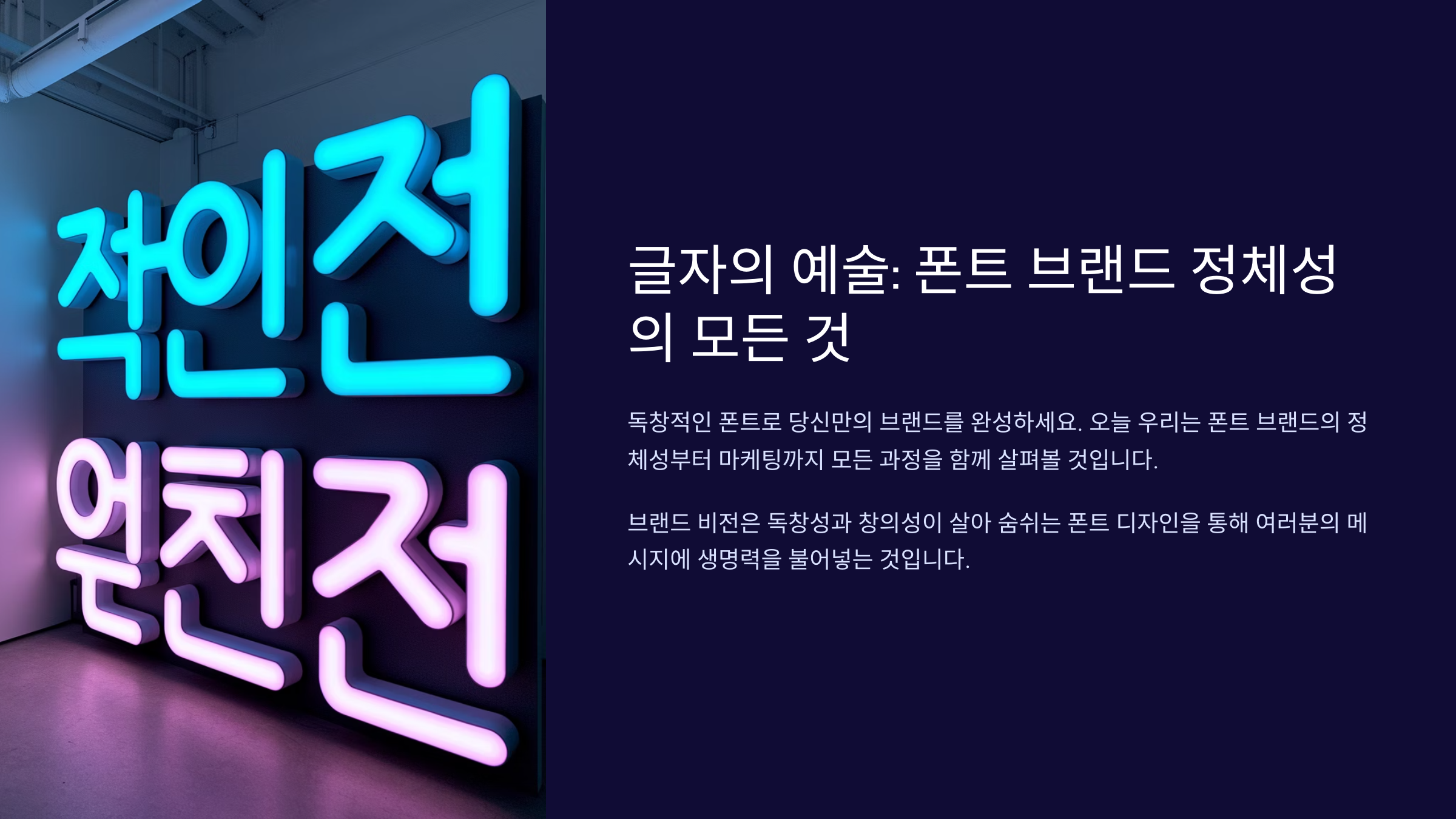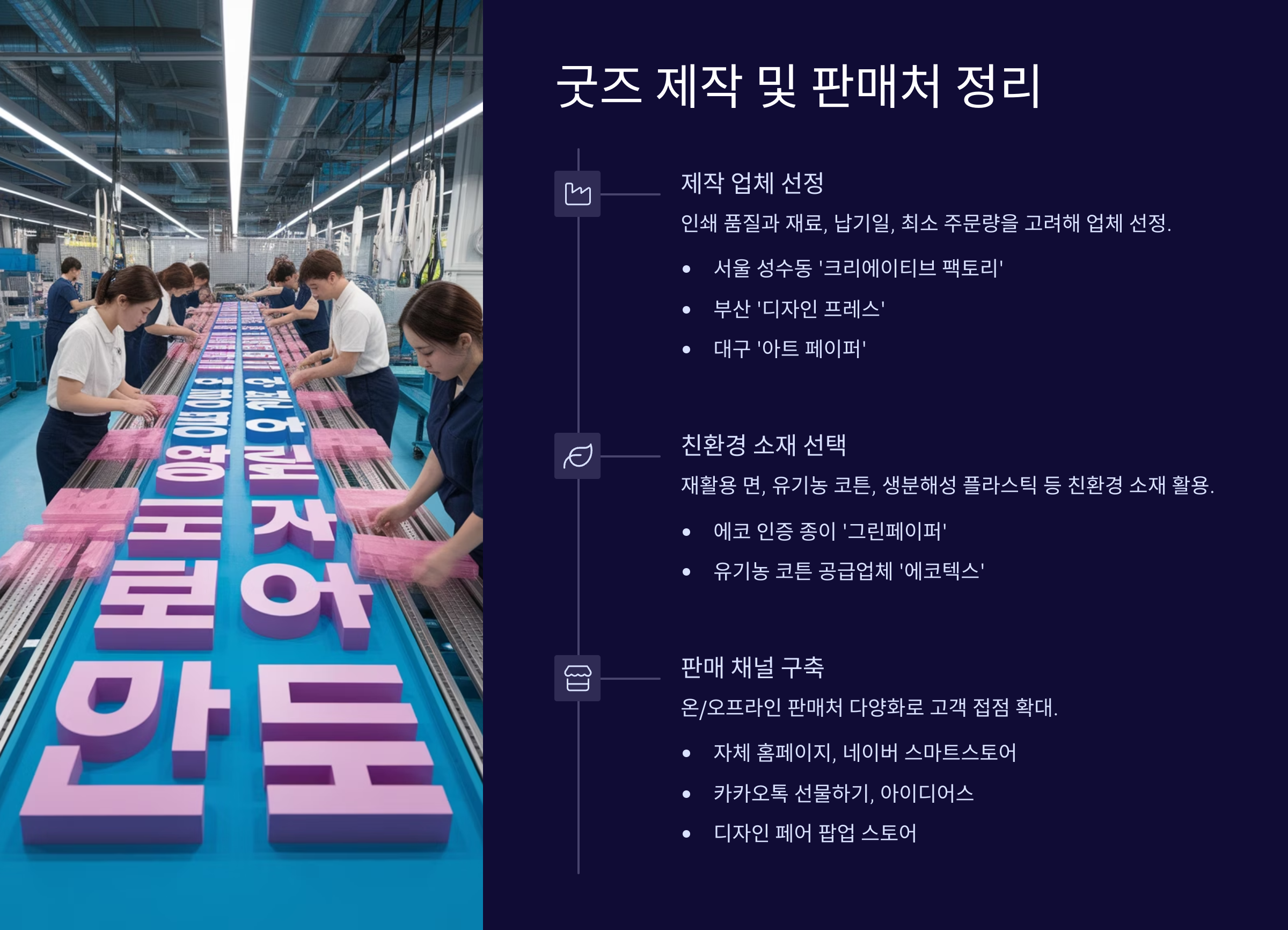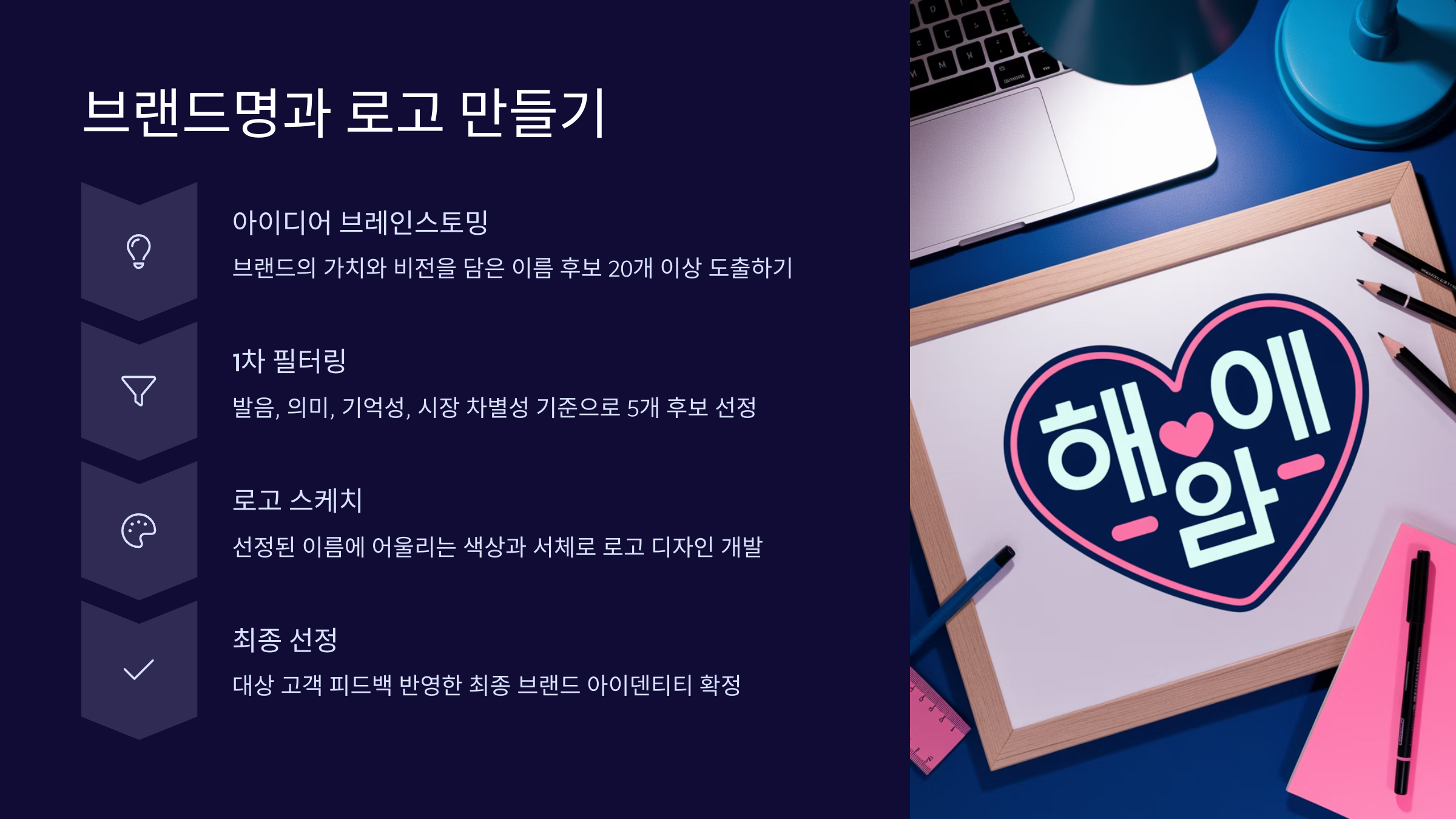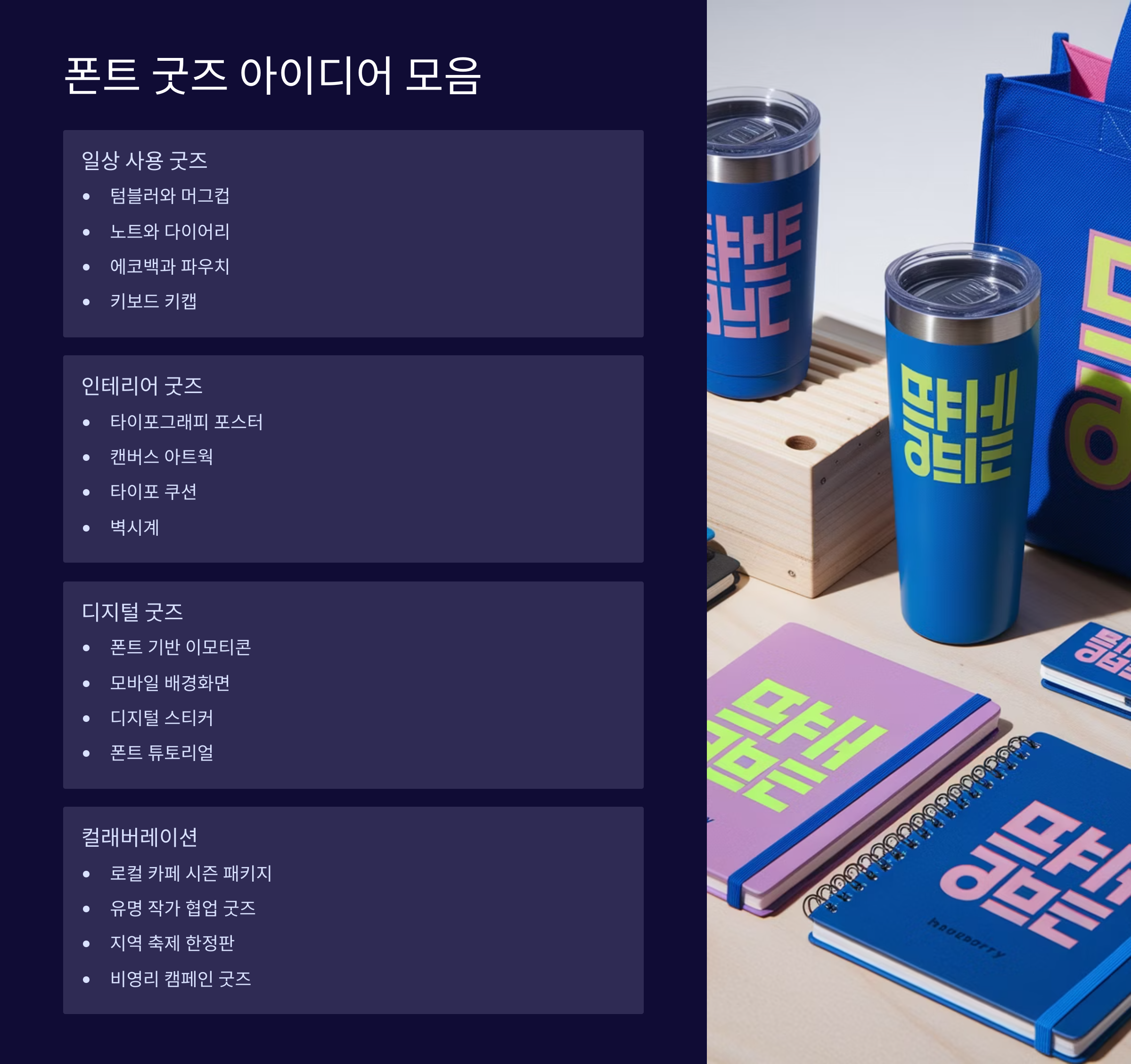
폰트를 만들었다면, 이제는 그 폰트로 브랜드를 만들어볼 차례예요. 단순히 글꼴이 아닌, 나만의 감성과 스타일을 담은 브랜드로 발전시킨다면 더 많은 사람들과 소통하고 수익도 창출할 수 있어요. 😊
특히 2025년 현재, 크리에이터들이 자신의 폰트를 활용한 굿즈 제작과 디지털 마켓 입점으로 활동 영역을 확장하고 있어요. '폰트 작가'라는 말이 생겨날 만큼, 폰트를 브랜드화하는 시대인 거죠! ✨
🏷 폰트 브랜드 정체성 잡기
브랜드는 단순한 이름이 아니라 ‘철학’이에요. 내가 만든 폰트가 전하고자 하는 메시지, 감성, 스타일을 스스로 명확하게 정의하는 게 첫걸음이에요. 폰트를 브랜드로 만들려면 이 정체성이 사람들에게도 느껴져야 하거든요. 💡
먼저, 폰트의 톤앤매너를 분석해봐요. 부드러운 손글씨라면 따뜻함, 귀여움, 일상감을 줄 수 있고, 고딕 스타일이라면 직선적이고 전문적인 인상을 줄 수 있어요. 이를 바탕으로 브랜드 성격을 다음과 같이 정의할 수 있어요:
– 감성 키워드: 따뜻함, 정직함, 위트, 세련됨 – 사용 타깃: 감성 블로거, 인디 출판, 온라인 셀러, 디자이너 – 연상되는 이미지: 책갈피, 노트, 손편지, 심플 아이콘 등
이런 식으로 나만의 브랜드 컨셉을 정해두면, 이후 굿즈나 웹페이지, 포트폴리오 구성에도 통일성을 줄 수 있어요. 그 감성이 브랜드가 되는 거죠. 🍃
🔍 폰트 브랜드 정체성 정리표
항목 예시 나만의 설정
폰트 성격 손글씨 / 단정함 / 레트로 감성적이고 빈티지한 느낌
브랜드 키워드 진심, 느림, 손맛 따뜻함, 일상
대상 고객 디자이너, 창작자 감성 굿즈 제작자
이렇게 브랜드 정체성을 정리하면, 이후 웹사이트, 인스타, 패키지 디자인까지 모두 연결돼요. 단순한 폰트가 아니라, ‘나의 브랜드’를 느끼게 만들어줄 수 있어요. ✨
✒ 브랜드명과 로고 만들기
브랜드 이름은 기억에 남고, 감성을 담을 수 있어야 해요. 글자체의 스타일을 표현하면서도 내가 추구하는 철학이 담긴 이름이 좋죠. 특히 폰트 브랜드라면 이름만으로도 서체 분위기를 떠올릴 수 있어야 해요. 🎨
예를 들어 ‘달빛체’, ‘모모서체’, ‘숨결 Sans’, ‘나무고딕’ 같은 이름은 서정적 느낌을 주고, ‘Noto Serif’, ‘Pretendard’, ‘TT Goryeong’ 같은 이름은 기능적·디자인적인 느낌을 줘요. 이름 짓기 전 이런 스타일을 먼저 정리해보세요.
로고는 브랜드의 얼굴이에요. 너무 복잡하지 않게, 폰트 이름을 활용한 ‘텍스트 로고’만 있어도 충분해요. 내가 만든 폰트로 브랜드명을 타이핑하고, 아이콘 한두 개만 넣어도 감성 가득한 로고가 완성된답니다! 🖌
로고 제작 툴은 Canva, Illustrator, Figma, 그리고 무료 로고 생성기들도 많이 있어요. 중요한 건 내 브랜드 무드보드(톤, 색상, 스타일)에 맞춰 일관성 있게 만드는 거예요.
🧠 브랜드명 네이밍 아이디어 예시
네이밍 패턴 예시 분위기
자연물 + 서체 나뭇잎체, 파도체 부드럽고 서정적
감정 + Sans 기쁨 Sans, 여유 Sans 모던하고 감성적
이름 기반 민정체, Arin Serif 작가 중심적
좋은 브랜드명은 내 폰트의 첫인상을 만들어줘요. 사람들이 그 이름을 듣고 이미지가 떠오른다면, 이미 브랜딩은 성공한 거예요. 그리고 그 이름을 내 폰트 로고로 직접 써보는 그 순간, 진짜 뿌듯함 폭발이죠. 💖
📁 폰트 브랜드 포트폴리오 구성
폰트를 만들었다면, 이제는 어떻게 보여줄지가 진짜 중요해요. 아무리 잘 만든 글자라도 '보여주는 방식'이 세련되지 않으면 주목받기 어렵거든요. 그래서 브랜딩의 연장선으로 포트폴리오 구성은 필수예요. 🧾
폰트 브랜드의 포트폴리오는 일반 디자이너 포폴과는 달라요. 서체의 용도, 톤, 적용 예시를 강조해야 해요. 대표적으로 다음 항목이 필수로 들어가요:
• 폰트 소개 이미지: 폰트 이름과 영문/한글 표기
• 문장 샘플: 감성적 문장 3~5줄 활용
• 폰트 구성표: 자음/모음/숫자/특수문자
• 실사용 예시: 명함, 엽서, 모바일, 패키지 등
🖼 폰트 포트폴리오 구성 예시
슬라이드 내용 필요 이유
01 커버 이미지 폰트 로고 + 배경사진 첫인상 전달
02 샘플 문장 감성 문장 타이포 구성 톤앤매너 보여주기
03 UI/굿즈 활용 앱화면, 엽서, 포스터 실용성 강조
Behance, 브런치, Notion 등 온라인 포트폴리오 플랫폼을 활용해보세요. 디자인 툴이 어렵다면 Canva로도 멋진 구성 가능하답니다! 폰트 포트폴리오는 내 폰트가 어디서 어떻게 쓰일 수 있는지를 상상하게 해주는 콘텐츠예요. ✨
🎁 폰트 굿즈 아이디어 모음
폰트는 ‘글자’일 뿐이라고요? 아니에요! 요즘은 폰트 하나로 다양한 굿즈 상품을 만들 수 있어요. 손글씨나 감성 서체는 특히 굿즈 제작에 잘 어울리고, 팬층까지 생기게 만들 수 있답니다. 💖
굿즈의 핵심은 ‘일상 속에서 만나는 폰트’예요. 그냥 PC에서 쓰는 폰트가 아니라, 엽서, 스티커, 패브릭, 머그잔 같은 아이템에 내 글씨가 담긴다면? 그건 진짜 세상 하나뿐인 브랜드가 되는 순간이에요. 😍
내가 생각했을 때 가장 활용도 높고 인기 있는 굿즈는 바로 스티커와 엽서예요. 제작비도 낮고, 감성도 전할 수 있고, 굿즈 초보도 도전하기 쉬운 제품이에요. 그 외에도 다음과 같은 아이템들을 추천해요:
📦 추천 굿즈 리스트
굿즈 종류 폰트 활용 포인트 제작 팁
엽서 세트 문장, 시구를 감성 글자와 함께 100장 단위 소량 인쇄 가능
스티커팩 짧은 문장, 말풍선, 단어 내지 + 커팅 포함
파우치/에코백 로고 또는 단어 중심 배치 패브릭 전사 인쇄 필요
굿즈는 단지 상품이 아니라 ‘내 폰트의 감성’을 실물로 전달하는 수단이에요. 사람 손에 들려 있는 내 글자, 카페 테이블에 올려진 내 머그컵을 상상해보세요! 진짜 감동이에요. 🥹
🏪 굿즈 제작 및 판매처 정리
폰트로 만든 굿즈, 어디서 만들고 어떻게 팔 수 있을까요? 다행히 요즘은 소량 제작도 가능하고, 개인 셀러도 쉽게 입점할 수 있는 플랫폼이 정말 많아요. 이젠 혼자서도 브랜드 굿즈샵 운영이 가능하다는 사실! 🤩
굿즈 제작은 보통 온라인 인쇄소에서 진행해요. 예: 마플샵, 미스터프린트, 디프린트, 비즈하우스 같은 플랫폼은 엽서, 스티커, 에코백, 머그컵까지도 아주 손쉽게 주문제작이 가능해요.
판매처는 두 가지로 나눠볼 수 있어요: ① 마켓 입점형 (예: 텀블벅, 스마트스토어, 29CM, 아이디어스) ② 프린트 연동형 (예: 마플샵, 레드버블, 픽사케이 등) 입점형은 내가 재고와 배송을 관리해야 하지만, 연동형은 주문이 들어오면 자동으로 제작+발송까지 되기 때문에 부담이 없어요. 🛍
🛒 굿즈 제작/판매 플랫폼 비교표
플랫폼 역할 장점 주의점
마플샵 제작 + 판매 1개부터 자동 판매 가능 마진이 낮을 수 있음
스마트스토어 판매 전용 국내 유저 많고 노출 높음 배송, 재고 직접 관리
아이디어스 핸드메이드 중심 판매 감성 굿즈 타깃에 적합 입점 심사 있음
특히 마플샵, 레드버블은 내 폰트를 활용한 이미지만 올리면 상품 자동화가 되기 때문에 처음 굿즈 만들기에 정말 좋아요. 디자이너들이 많이 쓰는 플랫폼이기도 하죠. 🖼
👉 다음은 마지막 실전 섹션! “SNS 및 온라인 마케팅 전략”으로, 내 브랜드와 굿즈를 사람들에게 알리는 방법을 정리해드릴게요.
📢 SNS 및 온라인 마케팅 전략
내가 만든 폰트와 굿즈, 이제는 사람들에게 보여줘야 해요! 지금은 ‘제품이 아무리 좋아도, 알려야 팔리는 시대’니까요. 그래서 SNS 마케팅은 폰트 브랜드에게 필수예요. 📱
먼저 플랫폼을 정하고 꾸준히 올리는 게 핵심이에요. 가장 추천하는 채널은 인스타그램, 트위터(X), 블로그(티스토리) 세 가지예요. 각각의 플랫폼에서 콘텐츠 스타일을 다르게 구성해보세요:
• 인스타그램 ➜ 감성 이미지 중심 (폰트 적용 예시, 스티커컷, 손글 문장)
• 블로그/티스토리 ➜ 제작 후기 + 다운로드 안내 + 상세 설명
• 트위터(X) ➜ 유머·짧은 텍스트 중심 바이럴 노림
또한, 요즘은 폰트 해시태그 검색이 매우 활성화돼 있어요. ‘#감성폰트 #무료폰트 #손글씨체 #폰트굿즈’ 같은 해시태그를 통해 사용자들에게 노출될 수 있으니 꼭 활용해보세요.
📈 SNS 마케팅 콘텐츠 구성 예시
콘텐츠 유형 내용 형식
폰트 문장컷 “오늘도 너를 그린다.” JPG/PNG 카드뉴스
제작 과정 공유 스케치부터 완성까지 릴스, 슬라이드
사용 예시 소개 사용자가 올린 사진 공유 리그램 or 리트윗
브랜드 초반에는 폰트를 무료로 배포하고, 굿즈는 선착순 이벤트로 진행해보는 것도 좋아요. 입소문 타는 가장 빠른 방법이기도 하거든요. DM, 이메일 리스트, 블로그 구독자도 꾸준히 늘려보세요! 💌
Q1. 폰트 하나만으로 브랜드를 만들 수 있나요?
A1. 물론이죠! 요즘은 감성 폰트 하나로 브랜딩, 굿즈, SNS 운영까지 가능해요. 서체가 곧 브랜드가 되는 시대예요. 😊
Q2. 폰트 굿즈 제작은 꼭 공장에서 해야 하나요?
A2. 전혀요! 온라인 인쇄 플랫폼(마플샵, 비즈하우스 등)에서 1개 단위부터 주문제작이 가능해요.
Q3. 폰트를 굿즈에 사용해도 라이선스 문제가 없을까요?
A3. 내가 직접 만든 폰트라면 자유롭게 사용 가능해요. 단, 타인이 만든 폰트라면 반드시 상업 사용 가능 여부를 확인해야 해요.
Q4. SNS에서 폰트 굿즈를 홍보할 때 효과적인 시간은 언제인가요?
A4. 일반적으로 오후 8~11시가 반응이 좋아요. 감성 문구나 작업물은 야간 타임에 더 몰입도를 얻을 수 있어요.
Q5. 판매 플랫폼 중 추천하는 곳은 어디인가요?
A5. 초보라면 마플샵, 텀블벅이 좋고, 운영 여력이 있다면 스마트스토어, 아이디어스도 추천해요.
Q6. 폰트 굿즈 가격은 어떻게 정하나요?
A6. 제작비 + 수수료 + 마진을 고려해 설정해요. 보통 2~3배 정도의 단가로 책정하면 안정적이에요.
Q7. 폰트 브랜드 포트폴리오를 어디에 올려야 할까요?
A7. Behance, 브런치, 티스토리, Notion이 많이 사용돼요. 이미지 중심으로 보기 좋은 곳이면 어디든 OK예요.
Q8. 폰트 굿즈 제작 후 고객 피드백은 어떻게 받나요?
A8. 폰트와 굿즈에 QR코드 또는 SNS 계정을 남겨 피드백을 유도해보세요. 구매 후기 이벤트도 좋은 방법이에요!
지금까지 폰트 브랜드 만들기부터 굿즈 제작과 마케팅까지 전 과정을 함께 알아봤어요. 단순한 폰트를 넘어서, '나만의 브랜드'로 키워가는 이 과정이 얼마나 재밌고 의미 있는지 느껴보셨죠? 💕
이제 당신의 폰트는 더 이상 단순한 글자가 아니에요. 세상에 감성을 전하고, 메시지를 담는 브랜드 자산이에요. 용기 내서 시작해보세요. 꾸준히 키우다 보면, 누군가는 당신의 글자를 보고 위로를 받을지도 몰라요. 🌈